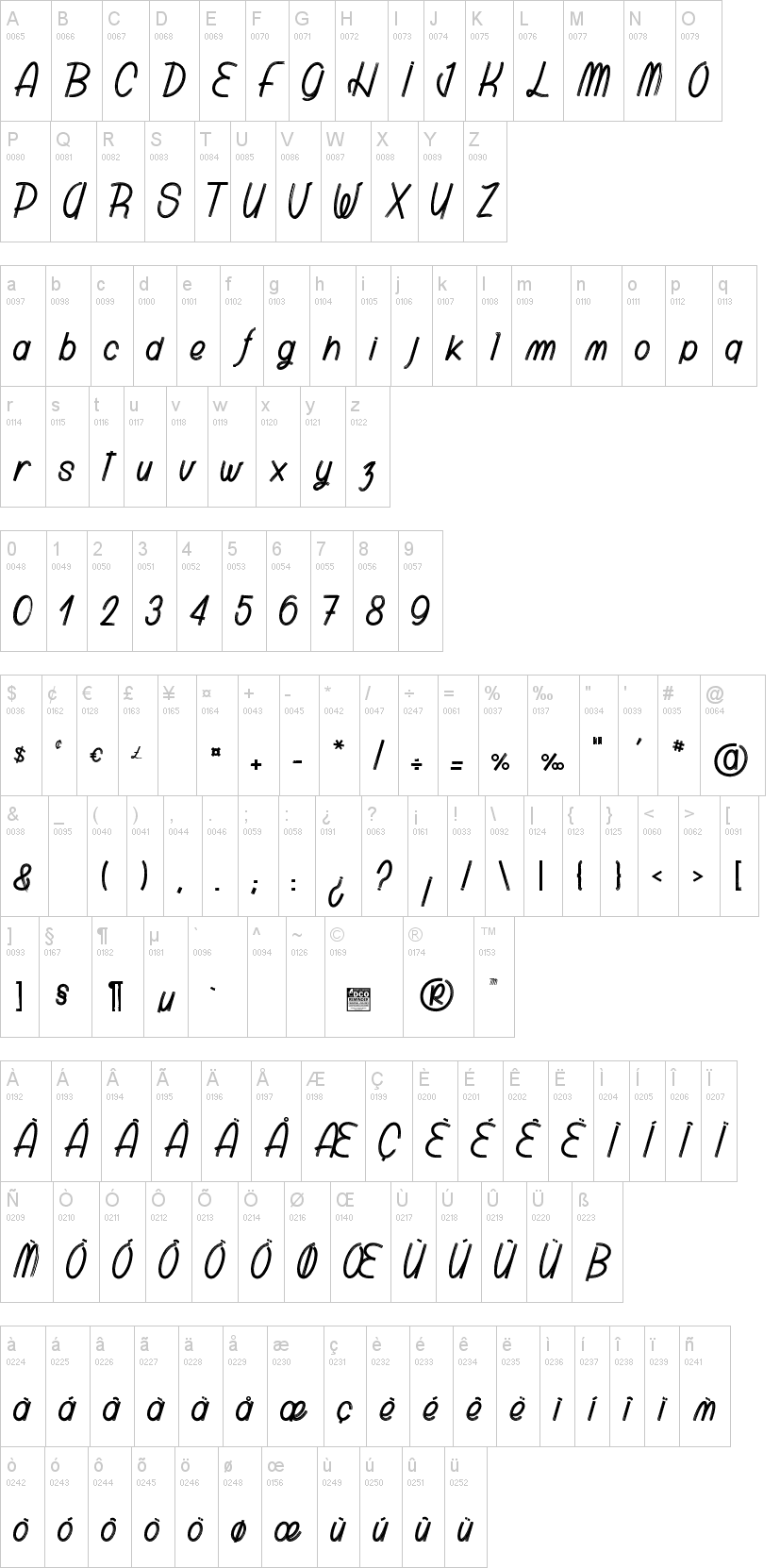
Polibrush
? Polibrush 字体是一款简约的手绘风格字体,它具有自然的流线型曲线,温柔的质感和活力四射的颜色,是一款非常适合用于卡通和插画制作的字体。它具有极具特色的外观,可以为您的作品带来更多的色彩和想象力,从而使您的作品充满活力和魅力。
Polibrush是一款非常不错的手写艺术字体,具有很好的视觉感,适合于文化类的宣传设计、商业类品牌的广告和产品包装设计以及个性化文字排版等较多场景。